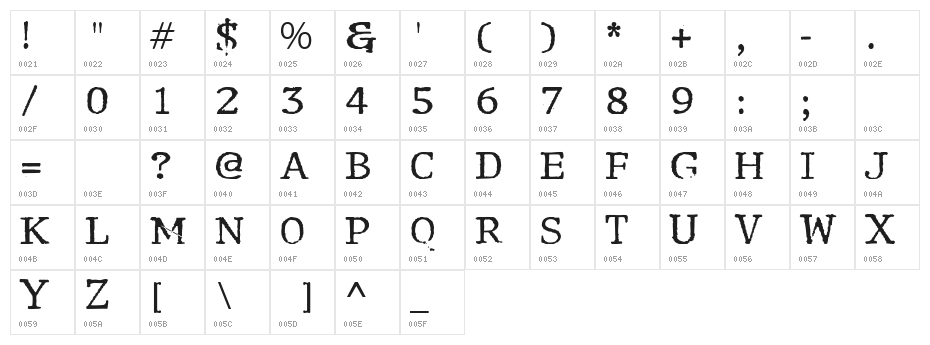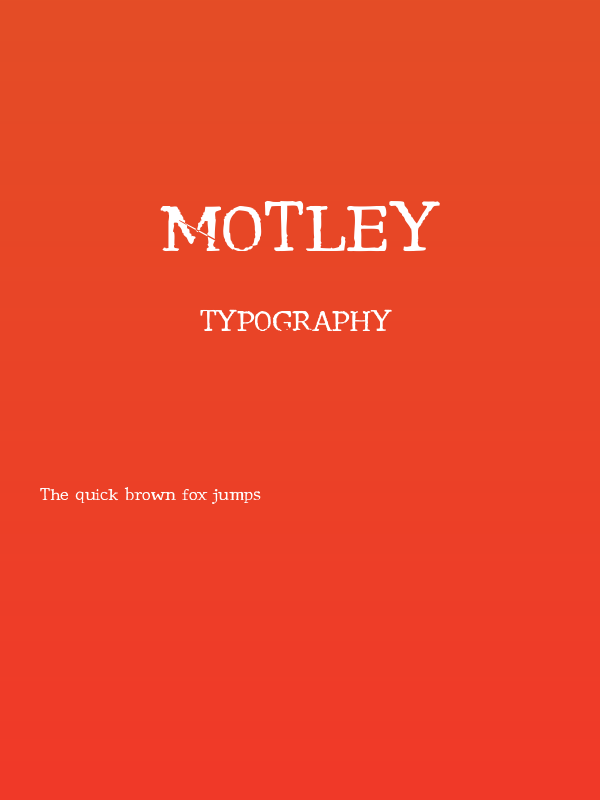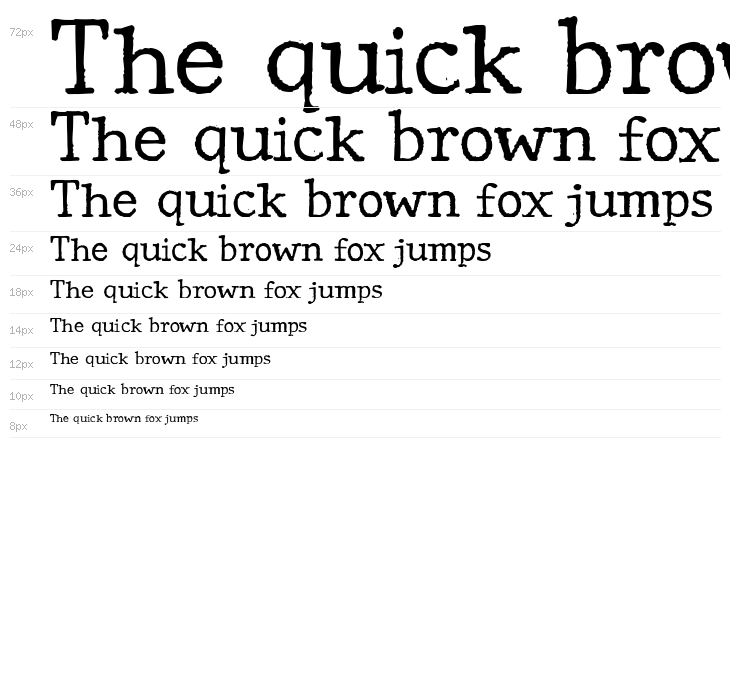
Motley Font
✎ Distorted Eroded
| श्रेणियाँ | Distorted Eroded |
| समग्र शैली | Vintage |
| उपयोग का मामला | Headlines, Logos, Posters |
| सुझाए गए प्रोजेक्ट | Ideal for vintage-themed posters, book covers, branding for artisanal products, and any project seeking a rustic or historical feel. |